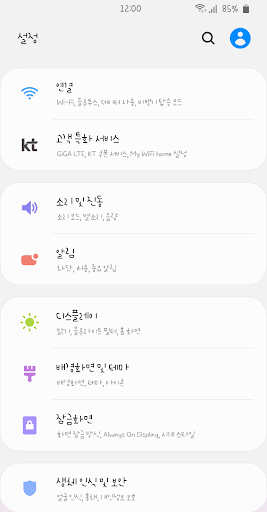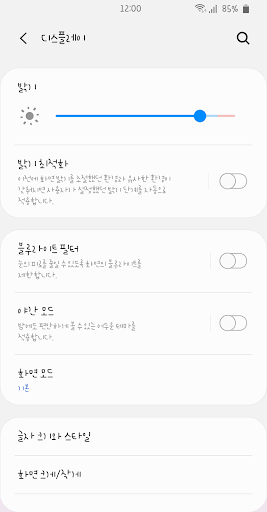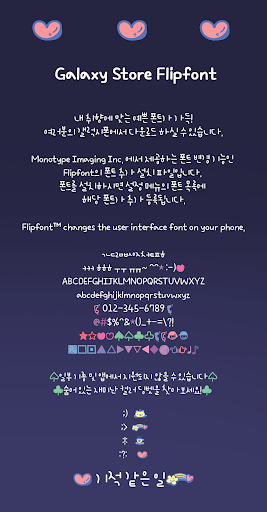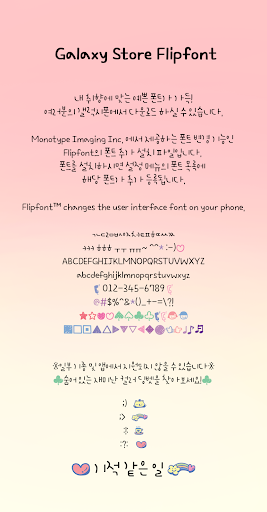
Ah기적같은일™ 한국어 Flipfont
[Ah기적같은일]은 자소들의 자연스러운 형태가 특징입니다.
글줄은 안정적인 중간 시각흐름으로 설정하여 가독성 또한 장문으로 사용시에도
시각적으로 무리 없도록 제작 하였습니다.
특별한 히든딩벳이 숨어져 있으니 찾아보시기 바랍니다. :>